みんなで明朝体てぬぐいを作ろう!
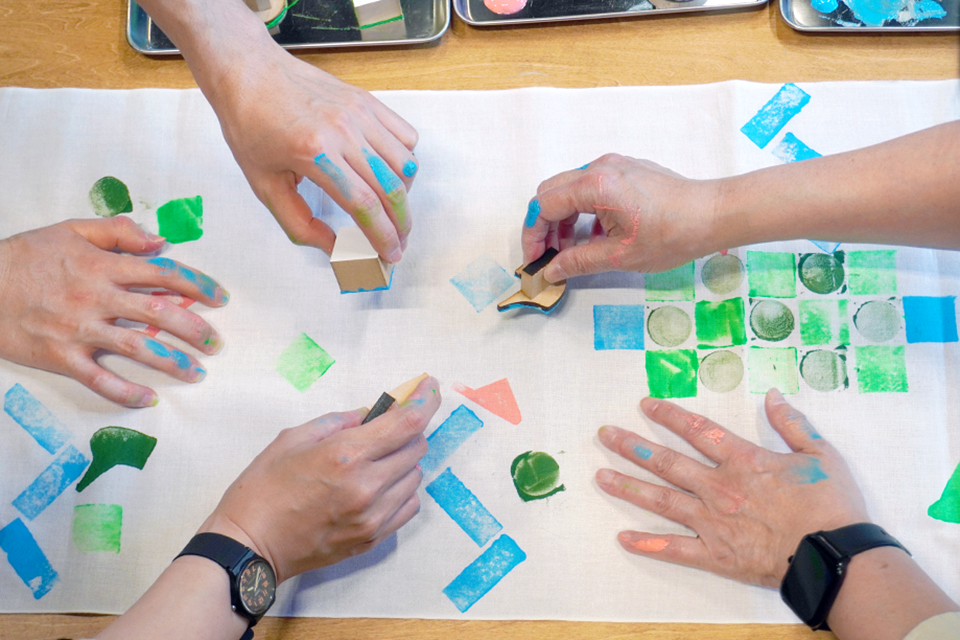
企画展「明朝体」関連イベントとして、参加者全員で力をあわせて明朝体てぬぐいを作りましょう! カットしていない手ぬぐい用の反物に、明朝体のエレメントで地模様をスタンプし、最後に明朝体展のグラフィックをシルクスクリーン印刷します。
企画展「明朝体」関連イベントとして、参加者全員で力をあわせて明朝体てぬぐいを作りましょう!
手ぬぐい用の反物を長く広げ、明朝体の点やハネ、ウロコなどのスタンプを思い思いに押して、手ぬぐいの地模様を作ります。最後にご自身で明朝体展のグラフィックをシルクスクリーン印刷し、その部分をカットしてお持ち帰りいただきます。どの地模様になるかは、作ったあとのお楽しみ!